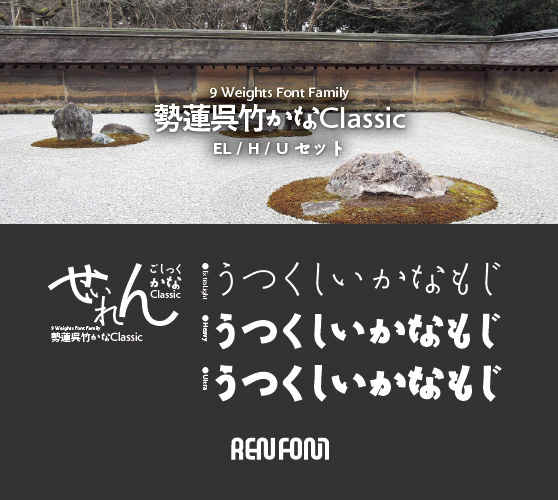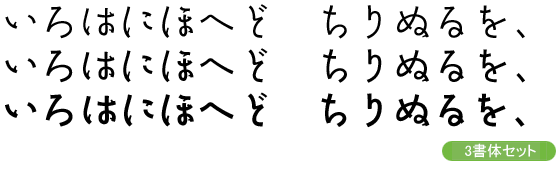
勢蓮呉竹仮名Classic-タイトル・大見出し用3ウェイトセット(EL/H/U)
「日本タイポグラフィ年鑑2001」受賞の仮名書体「勢蓮明朝-M」をブラッシュアップし、骨格にゴシックの特徴を加えて多ウェイト化した仮名書体。ゴシックでありながら和の雰囲気と潔さを兼ね備え、その文字の流れの流麗さが高級感を演出します。タイトル・大見出し用3ウェイトセット。
勢蓮呉竹仮名Classic-タイトル・大見出し用3ウェイトセット(EL/H/U)